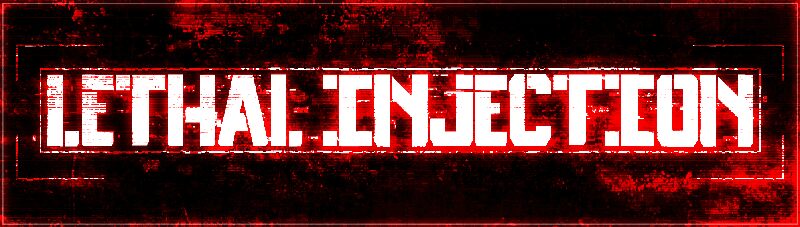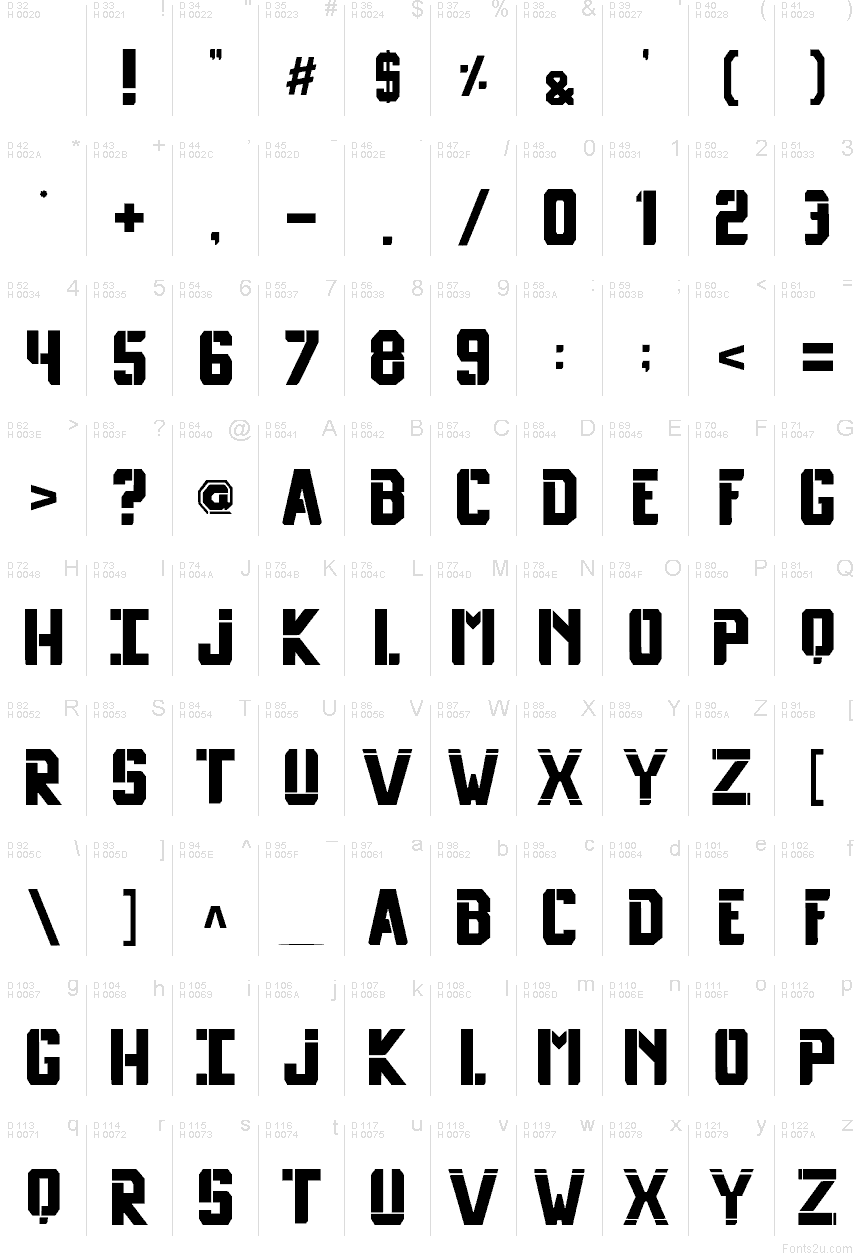
Lethal Injection Regular
Lethal Injection to darmowy krój pisma typu military display o surowym, industrialnym wyglądzie, zbudowany z wysokich blokowych liter o ostro ściętych narożnikach. Alfabet ma zdecydowany, plakatowy charakter – wąskie pionowe proporcje, ścięte łączenia i kanciaste otwory nadają wielkim literom zdyscyplinowany, stemplowany wygląd.
Idealnie sprawdzi się w logotypach gier, tytułach filmów akcji, grafikach streetwearowych, ulotkach eventowych oraz wszędzie tam, gdzie darmowy font musi mieć siłę przebicia, ale nie być typowym szabloniarskim pismem. Użyj go do krótkich nagłówków, nazw drużyn, emblematów czy monogramów, zwłaszcza jeśli zależy Ci, by litery wyglądały jak wycięte z metalu, a nie jak gładki, nowoczesny display.